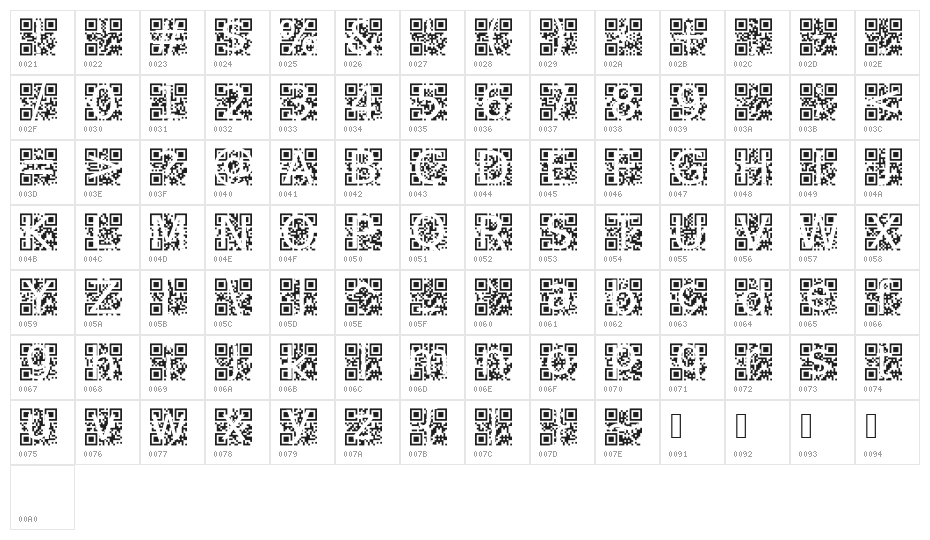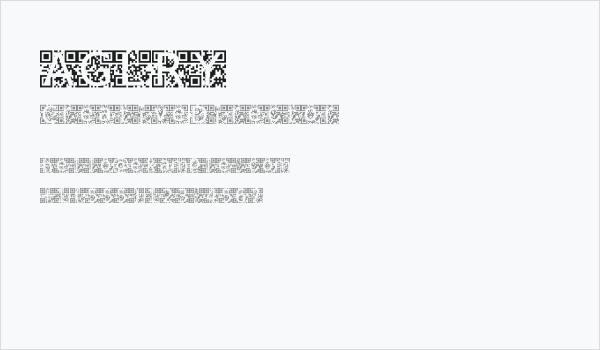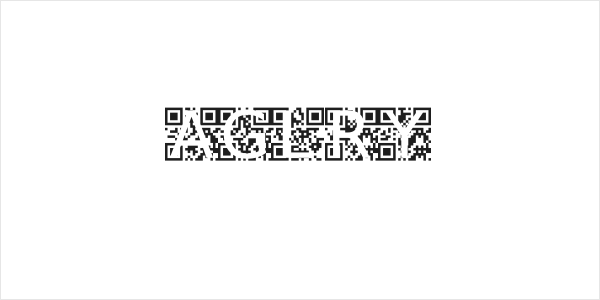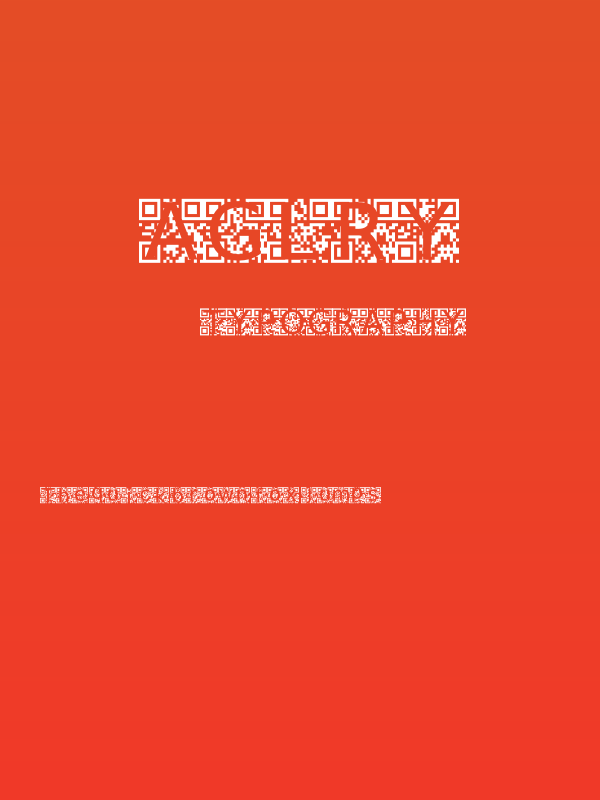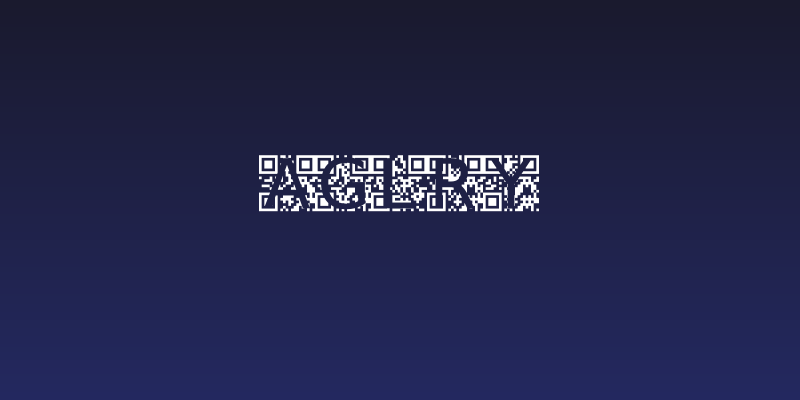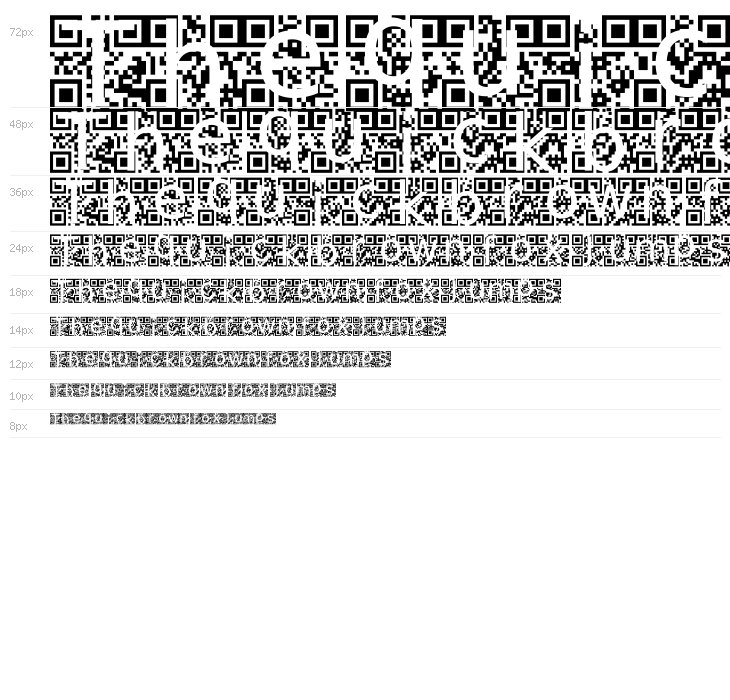
AGLRY Font
✎ Pixel
| Stile generale | Modern, Futuristic |
| Caso d'uso | Logos, Headlines, Digital Art |
| Progetti proposti | Ideal for digital art, tech-themed posters, video game graphics, or any project requiring a futuristic and digital aesthetic. |